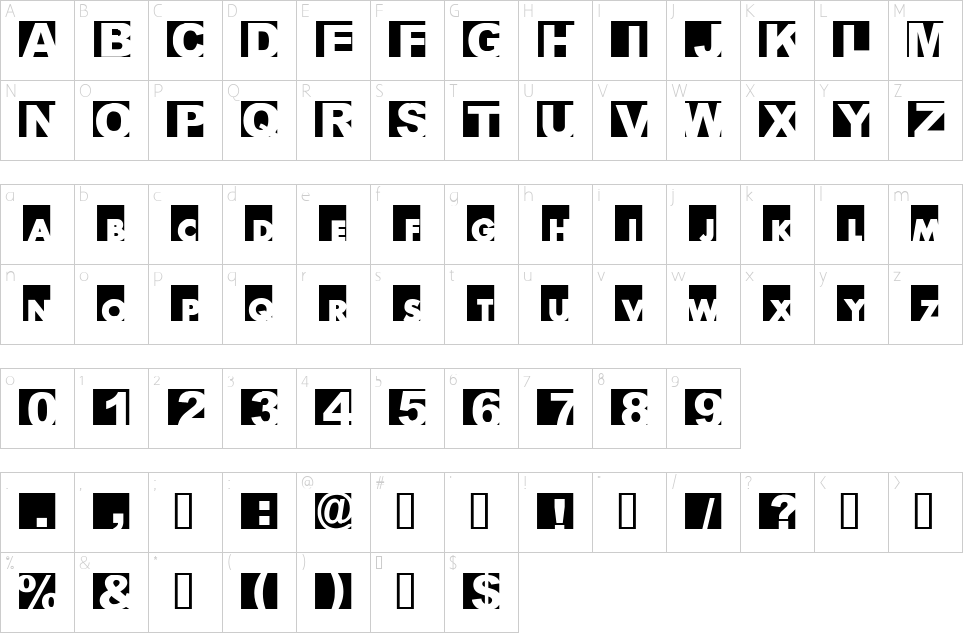
A fonte Big Arial é uma opção clara e legível para designers e profissionais de TI no Brasil e em todo o mundo. Desenvolvida por Dieter Schumacher, esta fonte se apresenta como um grande sucessor da popular Arial, mantendo a facilidade de leitura e elegância que a fonte original oferece. Com seu design limpo e sem ornamentos, a Big Arial é ideal para textos legíveis em grande escala, seja em websites, sites de redes sociais ou documentos. Foi uma das fontes mais populares na categoria de fontes gratuitas, tendo sido baixada 6.234 vezes, evidenciando sua qualidade e popularidade entre designers e desenvolvedores. Seja você um designer, programador ou editor de imagens, o Big Arial é uma excelente escolha para criar visuais profissionais e agradáveis.